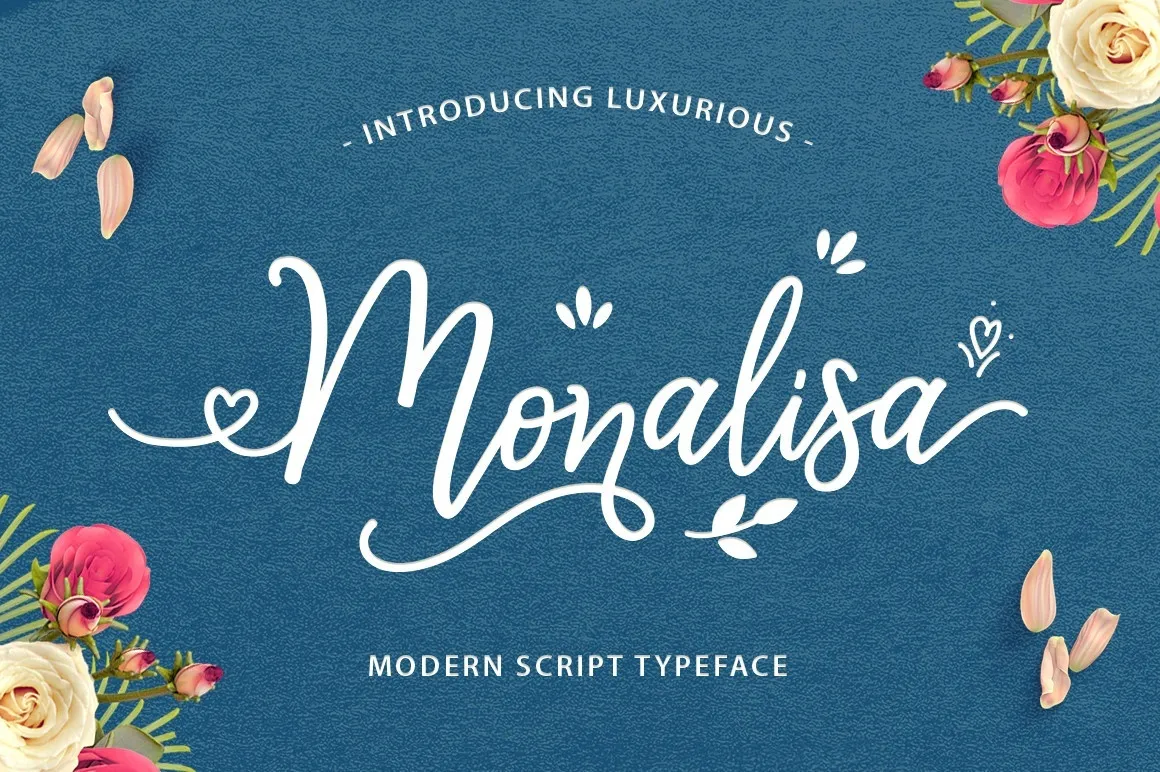
Monalisa Luxurious Script Font – Download Grátis
Aqui está uma descrição envolvente para a página de download da fonte ‘Monalisa Luxurious Script Font’: Introduzimos Monalisa Luxurious Script Font, um novo tipo tipográfico impressionante que trará um toque elegante aos seus projetos. Esta é uma opção moderna e luxuosa para qualquer design: seja para cartões de casamento, logotipos, cabeçalhos de site ou até mesmo desenhos de moda. Monalisa Script é perfeita para estilos que exigem delicadeza e sofisticação. Desenvolvida pelo designer Hamilton, esta fonte está disponível como um tipo monoline, contendo 413 caracteres gerais e 37 personagens com swashes. O conjunto completo inclui letras maiúsculas e minúsculas, uma ampla variedade de pontuação, números romanos e suporte multilíngue. Monalisa Luxurious é a escolha perfeita para aqueles que buscam um toque sofisticado em seus projetos digitais. Suas linhas finas e detalhes delicados criam um efeito visual luxuoso que vai tornar suas criações ainda mais únicas e memoráveis. Com sua elegância moderna e seu design cuidadosamente elaborado, Monalisa Luxurious oferece uma solução perfeita para designers em busca de personalidade e sofisticação no seu trabalho.